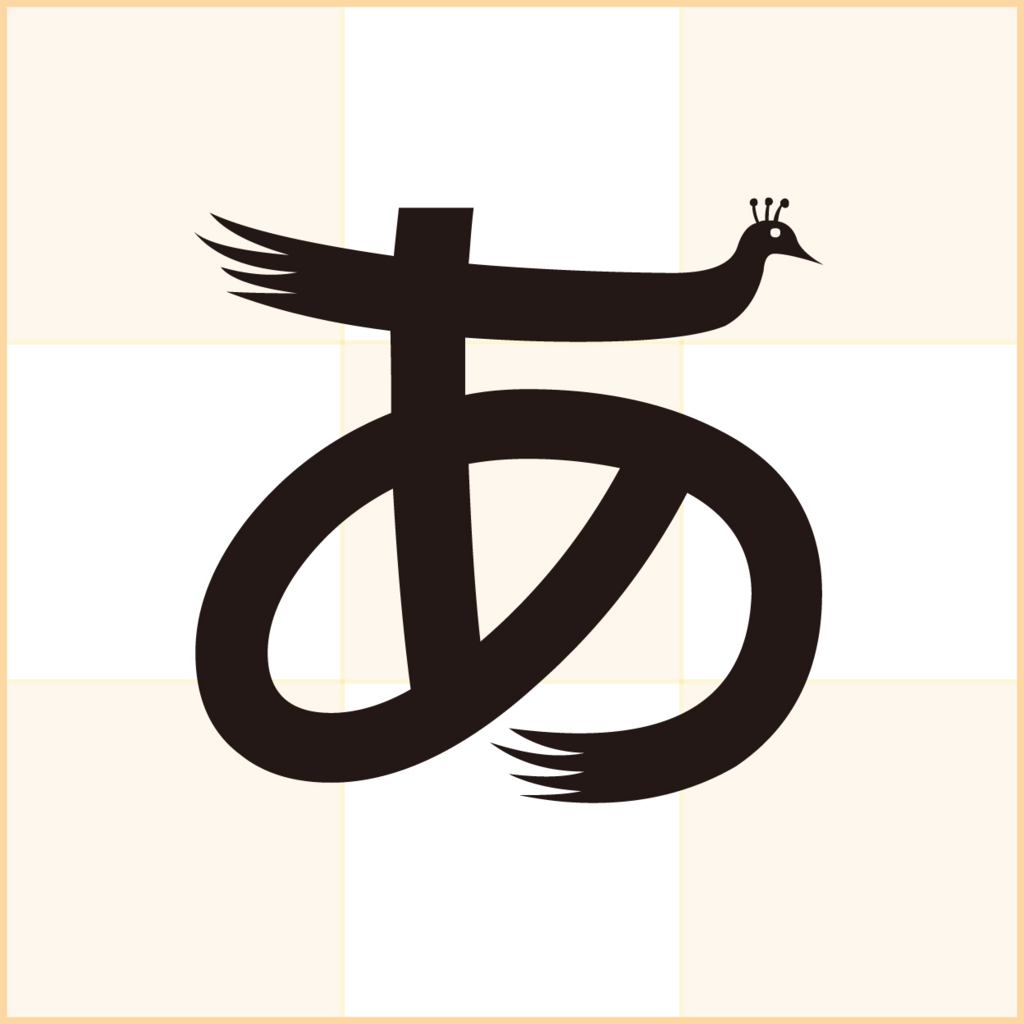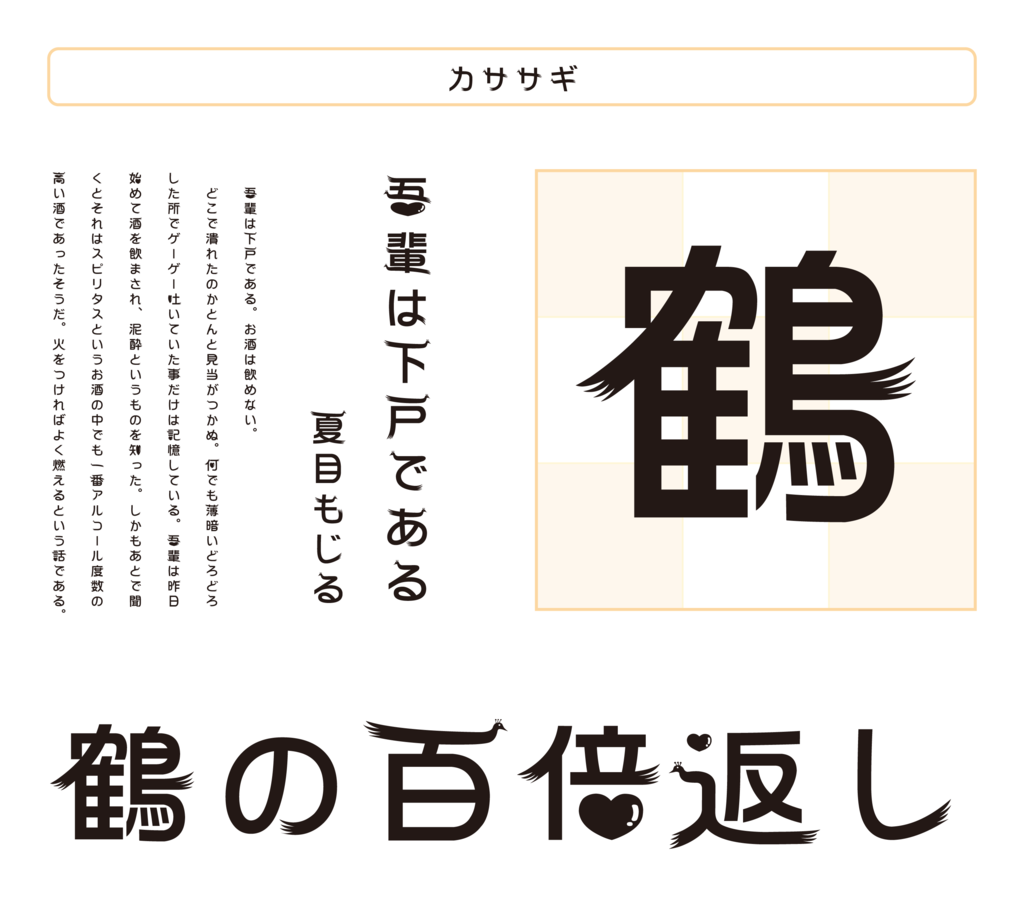
カササギ
見た目が孔雀のような字形の謎フォント。払いが羽、口(くち・くちへん)がハートマークになる特徴があるようだ。カササギを辞書で調べると、鳥綱スズメ目カラス科の1種の留鳥だそう。
ダイナフォントには処はいまいち使い処が分からない「謎フォント」が存在するが、このカササギは「鳥」関係で使用するのが良いのだろうか…。